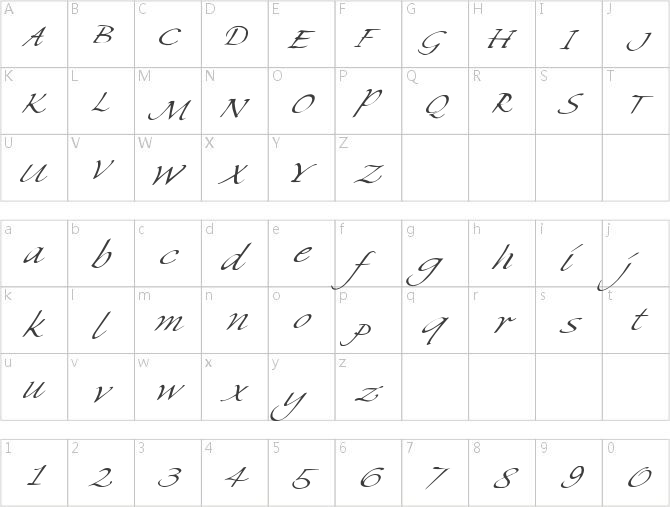
字體名稱: FZ HAND
FZ HAND 8 ITALIC
FZ HAND 8 ITALIC介紹
FZ HAND 8 ITALIC字體字庫是一款讓人賞心悅目、百看不厭的英文字體,適合各類廣告和產(chǎn)品包裝設(shè)計應(yīng)用,字體大小0.05MB,格式為ttf字體,上傳用戶是哼哼哈兮,作者/版權(quán)方為未知
FZ HAND 8 ITALIC效果圖